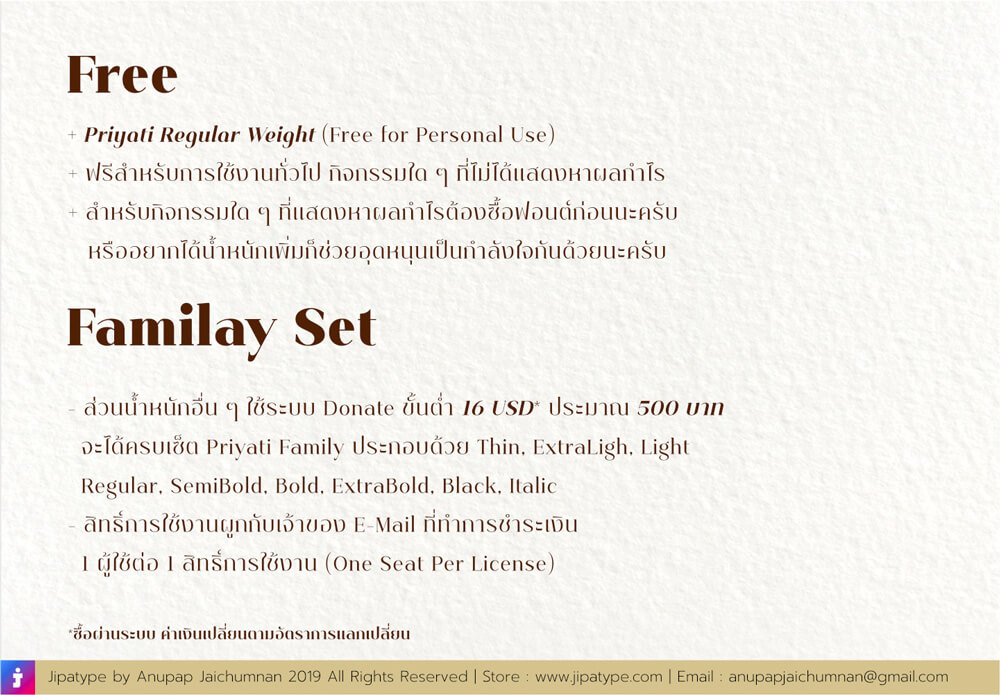
ป็นฟอนต์ที่ได้รับแรงบันดาลใจมาจากตัวอักษรหน้าปกสมุดนักเรียน
ผมคิดว่ามันสวยดีเลยลองหาแบบอักษรที่คล้าย ๆ กันมาเป็น Ref ในการออกแบบชุดตัวอักษรนี้
จึงหาชื่อที่เข้ากับคำว่า การศึกษา การเรียนรู้ จึงได้ชื่อ ปริยัติ ในภาษาบาลีแปลว่า การเล่าเรียน
เทียบอักษรโรมันก็เลยได้เป็น Priyati